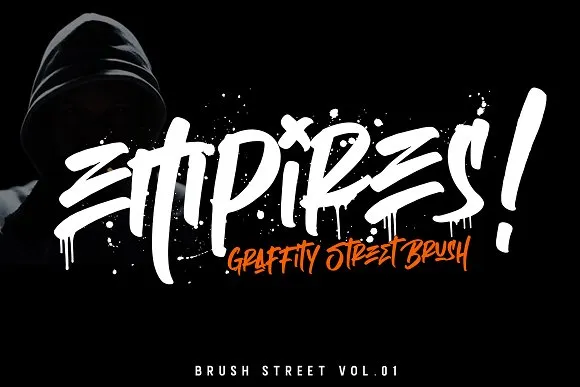
Empires Brush Font – Download Grátis
A Empires Brush Font é uma nova escolha para designers que buscam adicionar a um estilo urbano e agitado às suas criações digitais. Este tipo digital vem diretamente das ruas, fornecendo uma combinação de energia e frescura vibrante, ideal para qualquer aplicação gráfica que necessite de um revestimento moderno. Seja em logotipos, roupas, camisetas, capas de hoodie ou até mesmo na embalagem de produtos, a Empires Brush Font é perfeita para dar um upgrade visual e tornar seu design mais contemporâneo. Para aqueles que buscam algo novo e vibrante, esta fonte digital é uma excelente escolha para se juntar à sua coletânea de fontes digitais.